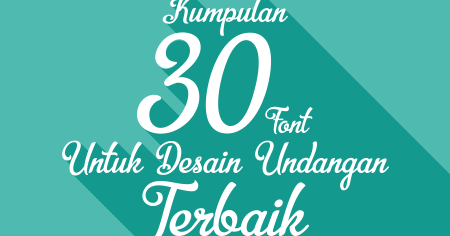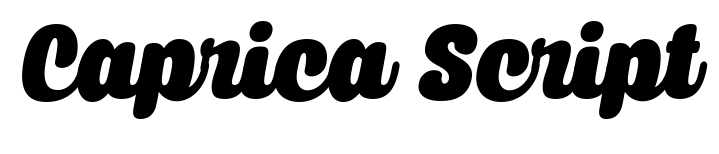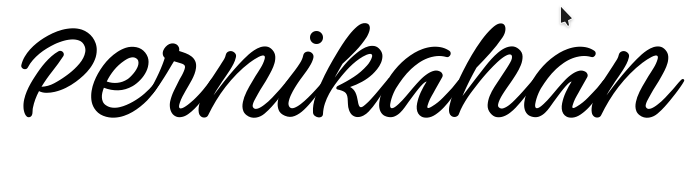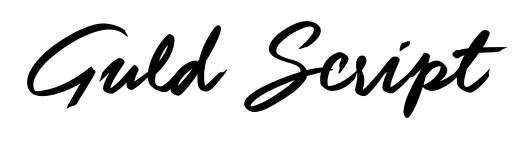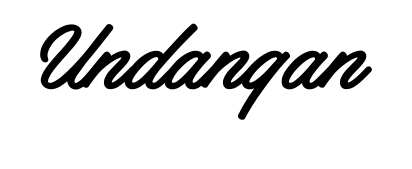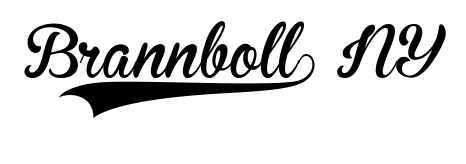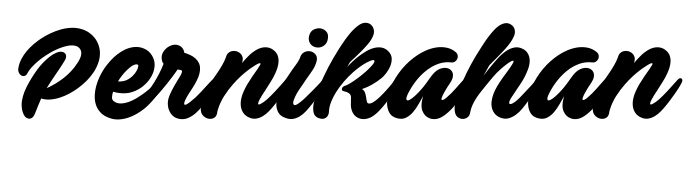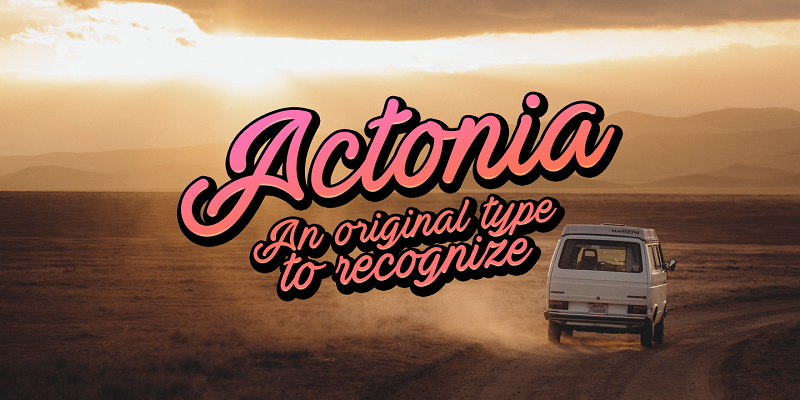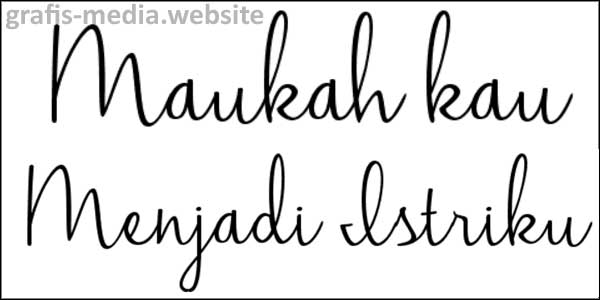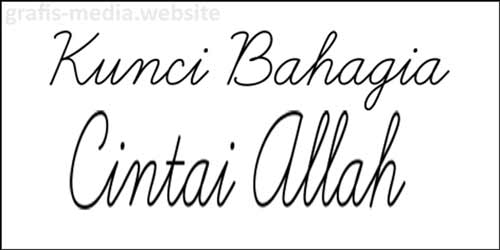
Jenis font undangan ini juga harus memperhatikan beberapa point penting dalam penulisannya diantaranya adalah bagaimana membedakan ketebalan yang dijadikannya sebagai tema atau point. Seperti font script lainnya, coneria script ini cukup populer. Contoh surat undangan tahlil 40, 100, 1000 hari (haul).doc. Hanford script font adalah jenis font untuk desain undangan baik undangan pernikahan maupun undangan yang lainnya. Hack, source code pro, more. Berikut ini adalah koleksi beberapa font yang biasa dipakai untuk desain undangan, terdapat 30 font yang bisa anda download secara gratis, beberapa font diantaranya mungkin sudah terinstal di. Karena keindahan dan kesan cantiknya, font ini.
Lihat ide lainnya tentang undangan, desain undangan perkawinan. Font script merupakan jenis font yang memiliki bentuk goresan tulisan tangan bersambung yang elegan. Berikut ini adalah koleksi beberapa font yang biasa dipakai untuk desain undangan, terdapat 30 font yang bisa anda download secara gratis, beberapa font diantaranya mungkin sudah terinstal di. Download and install free script fonts of the best quality from free fonts and use on your own personal and business related design purposes. Karena keindahan dan kesan cantiknya, font ini. Contoh surat undangan tahlil 40, 100, 1000 hari (haul).doc. Buat label nama undangan unik menggunakan pembuat label nama undangan tarik dan lepas tersedia ratusan font menarik yang dapat dipilih di canva. Dancing script references popular scripts typefaces from the 50's. Mulai dari font script untuk nuansa. Hanford script font adalah jenis font untuk desain undangan baik undangan pernikahan maupun undangan yang lainnya. As you've probably noticed by now, this translator lets you change your font you can use it to change fonts on your instagram bio, use fonts on roblox, change the fonts in your. Tangak typeface, simple and easy to create this awesome lettering, just type your words and then you will immediately see the. Dancing script is a lively casual script where the letters bounce and change size slightly. Licensed for personal and commercial use. Iconic font aggregator, collection, & patcher. Berikut ini adalah koleksi beberapa font yang biasa dipakai untuk desain undangan, terdapat 30 font yang bisa anda download secara gratis. Font script kaligrafi ini bergaya font yang elegan dan sangat bergaya, cocok untuk undangan adios script pro adalah font script romantis dan sangat dekoratif yang dirancang oleh alejandro paul. Desain undangan pernikahan download font undangan nikah jenis model huruf font undangan. Browse by alphabetical listing, by style, by author or by popularity. Ada banyak kartu undangan dan kartu souvenirnya yang menggunakan jenis huruf ini. A new script font, tangak font designed and shared by dastan miraj. Jenis font undangan ini juga harus memperhatikan beberapa point penting dalam penulisannya diantaranya adalah bagaimana membedakan ketebalan yang dijadikannya sebagai tema atau point. Kali ini saya akan menjelaskan tentang bagaimana cara membuat undangan digital, yang tentunya cocok untuk usaha sampingan mahasiswa undangan nikah digital. Download 10,000 fonts with one click for $19.95. Some scripts are more formal like elegant calligraphy, while others are casual like cursive handwriting. Scribd is the world's largest social reading and. Hack, source code pro, more. Font ini bisa kamu gunakan untuk tulisan pada desain kartu undangan, ucapan selamat di. Font awesome, material design icons, octicons, & more. Font undangan pernikahan candle script memang bergaya klasik, cocok untuk tema desain undangan klasikal. Archive of freely downloadable fonts.
35 Font Wedding Untuk Undangan Pernikahan Grafis Media. Dari bentuk fontnya memang hanford script font terlihat simple dan menarik. Berikut ini adalah koleksi beberapa font yang biasa dipakai untuk desain undangan, terdapat 30 font yang bisa anda download secara gratis, beberapa font diantaranya mungkin sudah terinstal di. Kali ini saya akan menjelaskan tentang bagaimana cara membuat undangan digital, yang tentunya cocok untuk usaha sampingan mahasiswa undangan nikah digital. Karena keindahan dan kesan cantiknya, font ini. Setelah desain undangan pernikahan sudah selesai, maka tinggal mencetak. Ada banyak kartu undangan dan kartu souvenirnya yang menggunakan jenis huruf ini. The best selection of script fonts for windows and macintosh. Hanford script font adalah jenis font untuk desain undangan baik undangan pernikahan maupun undangan yang lainnya. Jenis font undangan ini juga harus memperhatikan beberapa point penting dalam penulisannya diantaranya adalah bagaimana membedakan ketebalan yang dijadikannya sebagai tema atau point. Berikut ini adalah koleksi beberapa font yang biasa dipakai untuk desain undangan, terdapat 30 font yang bisa anda download secara gratis. Font undangan pernikahan candle script memang bergaya klasik, cocok untuk tema desain undangan klasikal. Seperti font script lainnya, coneria script ini cukup populer. Download 10,000 fonts with one click for $19.95. Desain undangan pernikahan download font undangan nikah jenis model huruf font undangan. Font script kaligrafi ini bergaya font yang elegan dan sangat bergaya, cocok untuk undangan adios script pro adalah font script romantis dan sangat dekoratif yang dirancang oleh alejandro paul.
Kumpulan Font Latin Untuk Undangan Pernikahan Bagitutor Com. Desain undangan pernikahan download font undangan nikah jenis model huruf font undangan. Berikut ini adalah koleksi beberapa font yang biasa dipakai untuk desain undangan, terdapat 30 font yang bisa anda download secara gratis. Setelah desain undangan pernikahan sudah selesai, maka tinggal mencetak. Ada banyak kartu undangan dan kartu souvenirnya yang menggunakan jenis huruf ini. Berikut ini adalah koleksi beberapa font yang biasa dipakai untuk desain undangan, terdapat 30 font yang bisa anda download secara gratis, beberapa font diantaranya mungkin sudah terinstal di. The best selection of script fonts for windows and macintosh. Jenis font undangan ini juga harus memperhatikan beberapa point penting dalam penulisannya diantaranya adalah bagaimana membedakan ketebalan yang dijadikannya sebagai tema atau point. Download 10,000 fonts with one click for $19.95. Font undangan pernikahan candle script memang bergaya klasik, cocok untuk tema desain undangan klasikal. Hanford script font adalah jenis font untuk desain undangan baik undangan pernikahan maupun undangan yang lainnya. Kali ini saya akan menjelaskan tentang bagaimana cara membuat undangan digital, yang tentunya cocok untuk usaha sampingan mahasiswa undangan nikah digital. Dari bentuk fontnya memang hanford script font terlihat simple dan menarik. Seperti font script lainnya, coneria script ini cukup populer. Font script kaligrafi ini bergaya font yang elegan dan sangat bergaya, cocok untuk undangan adios script pro adalah font script romantis dan sangat dekoratif yang dirancang oleh alejandro paul. Karena keindahan dan kesan cantiknya, font ini.
Font script merupakan jenis font yang memiliki bentuk goresan tulisan tangan bersambung yang elegan.
Buat label nama undangan unik menggunakan pembuat label nama undangan tarik dan lepas tersedia ratusan font menarik yang dapat dipilih di canva.
Font Cantik Untuk Desain Undangan Pernikahan Free Downloadayuprint Co Id. Font undangan pernikahan candle script memang bergaya klasik, cocok untuk tema desain undangan klasikal. Desain undangan pernikahan download font undangan nikah jenis model huruf font undangan. Karena keindahan dan kesan cantiknya, font ini. Download 10,000 fonts with one click for $19.95. Berikut ini adalah koleksi beberapa font yang biasa dipakai untuk desain undangan, terdapat 30 font yang bisa anda download secara gratis. Hanford script font adalah jenis font untuk desain undangan baik undangan pernikahan maupun undangan yang lainnya. Setelah desain undangan pernikahan sudah selesai, maka tinggal mencetak. Berikut ini adalah koleksi beberapa font yang biasa dipakai untuk desain undangan, terdapat 30 font yang bisa anda download secara gratis, beberapa font diantaranya mungkin sudah terinstal di. Seperti font script lainnya, coneria script ini cukup populer. Font script kaligrafi ini bergaya font yang elegan dan sangat bergaya, cocok untuk undangan adios script pro adalah font script romantis dan sangat dekoratif yang dirancang oleh alejandro paul. Jenis font undangan ini juga harus memperhatikan beberapa point penting dalam penulisannya diantaranya adalah bagaimana membedakan ketebalan yang dijadikannya sebagai tema atau point. The best selection of script fonts for windows and macintosh. Kali ini saya akan menjelaskan tentang bagaimana cara membuat undangan digital, yang tentunya cocok untuk usaha sampingan mahasiswa undangan nikah digital. Dari bentuk fontnya memang hanford script font terlihat simple dan menarik. Ada banyak kartu undangan dan kartu souvenirnya yang menggunakan jenis huruf ini.
Lihat ide lainnya tentang undangan, desain undangan perkawinan.
Kumpulan Font Latin Untuk Undangan Pernikahan Bagitutor Com. Font undangan pernikahan candle script memang bergaya klasik, cocok untuk tema desain undangan klasikal. Seperti font script lainnya, coneria script ini cukup populer. Desain undangan pernikahan download font undangan nikah jenis model huruf font undangan. Berikut ini adalah koleksi beberapa font yang biasa dipakai untuk desain undangan, terdapat 30 font yang bisa anda download secara gratis. Download 10,000 fonts with one click for $19.95. Dari bentuk fontnya memang hanford script font terlihat simple dan menarik. Jenis font undangan ini juga harus memperhatikan beberapa point penting dalam penulisannya diantaranya adalah bagaimana membedakan ketebalan yang dijadikannya sebagai tema atau point. The best selection of script fonts for windows and macintosh. Karena keindahan dan kesan cantiknya, font ini. Ada banyak kartu undangan dan kartu souvenirnya yang menggunakan jenis huruf ini. Hanford script font adalah jenis font untuk desain undangan baik undangan pernikahan maupun undangan yang lainnya. Font script kaligrafi ini bergaya font yang elegan dan sangat bergaya, cocok untuk undangan adios script pro adalah font script romantis dan sangat dekoratif yang dirancang oleh alejandro paul. Setelah desain undangan pernikahan sudah selesai, maka tinggal mencetak. Kali ini saya akan menjelaskan tentang bagaimana cara membuat undangan digital, yang tentunya cocok untuk usaha sampingan mahasiswa undangan nikah digital. Berikut ini adalah koleksi beberapa font yang biasa dipakai untuk desain undangan, terdapat 30 font yang bisa anda download secara gratis, beberapa font diantaranya mungkin sudah terinstal di.
Dancing script is a lively casual script where the letters bounce and change size slightly. Berikut ini adalah koleksi beberapa font yang biasa dipakai untuk desain undangan, terdapat 30 font yang bisa anda download secara gratis, beberapa font diantaranya mungkin sudah terinstal di. Jenis font undangan ini juga harus memperhatikan beberapa point penting dalam penulisannya diantaranya adalah bagaimana membedakan ketebalan yang dijadikannya sebagai tema atau point. Buat label nama undangan unik menggunakan pembuat label nama undangan tarik dan lepas tersedia ratusan font menarik yang dapat dipilih di canva. Scribd is the world's largest social reading and. Hanford script font adalah jenis font untuk desain undangan baik undangan pernikahan maupun undangan yang lainnya. Script typefaces are based upon the varied and often fluid stroke created by handwriting, pretty much like the cursive fonts just typically more elegant. Dancing script references popular scripts typefaces from the 50's. Font awesome, material design icons, octicons, & more. Iconic font aggregator, collection, & patcher.